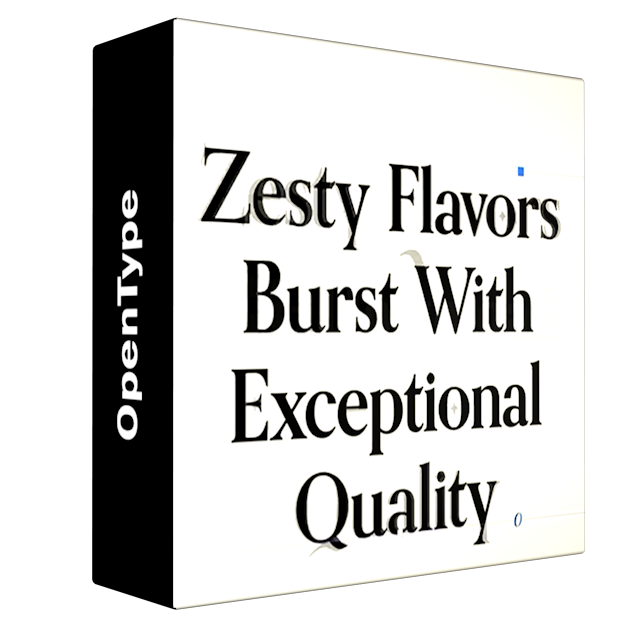
Typography Advanced Font Techniques
В этом курсе Найджел Френч приглашает вас в путешествие, чтобы исследовать нюансы и тонкости типографики. Узнайте, как — и, что еще важнее, почему и когда — использовать дискреционные лигатуры, альтернативные символы, стилистические наборы, орнаменты, символы росчерка, альтернативные заголовки и многие другие типографские изыски. К концу курса вы будете знать, где найти и как использовать полный спектр опций OpenType, чтобы добавить изюминку и индивидуальность вашей работе. Вы также поймете сильные стороны и ограничения вариативных шрифтов и цветных шрифтов.